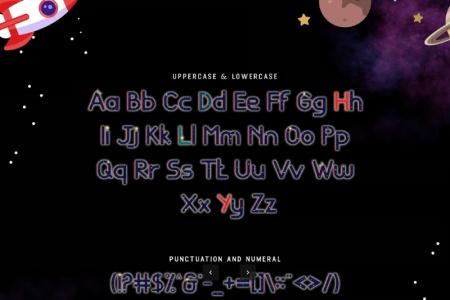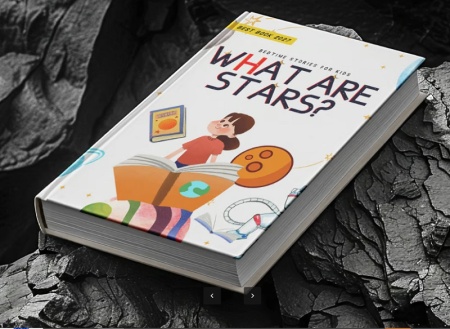
فونت انگلیسی فانتزی فضانورد Spacelight
فونت انگلیسی فانتزی فضانورد
فونت انگلیسی فانتزی فضانورد با نام Spacelight از جی اف ایکس دانلود. این فونت انگلیسی فضایی با طراحی فانتزی حس ماجراجویی و رمزآلودی را منتقل می‌کنند. مناسب برای طراحی های گرافیکی علمی تخیلی و آینده‌نگرانه، طراحی لوگو برای بازی‌های ویدیویی، طراحی پوستر برای فیلم‌های علمی تخیلی، طراحی وبسایت‌های مرتبط با فضا و غیره می باشد.
✅ نام فونت انگلیسی: Spacelight - Unique Decorative Font